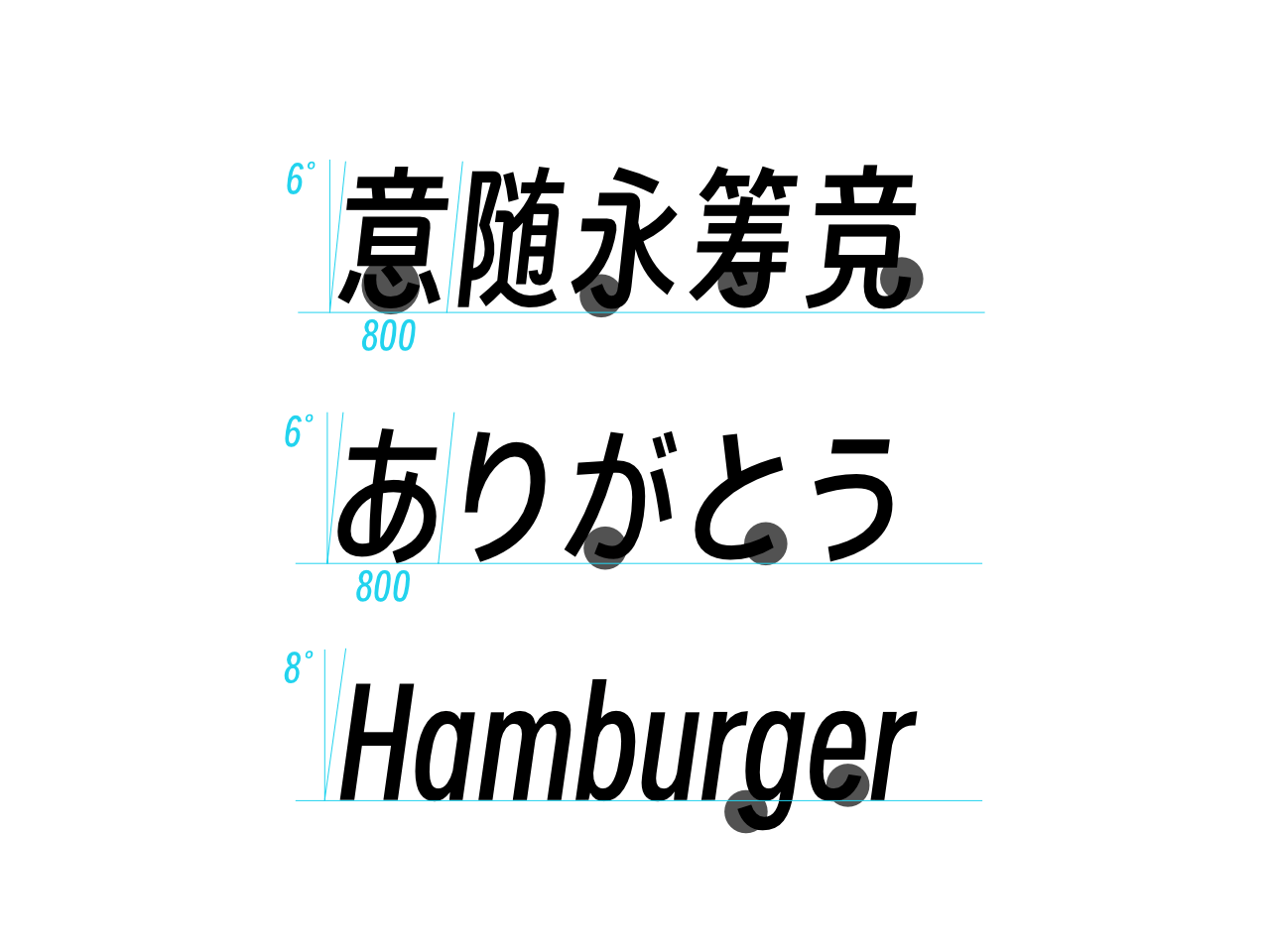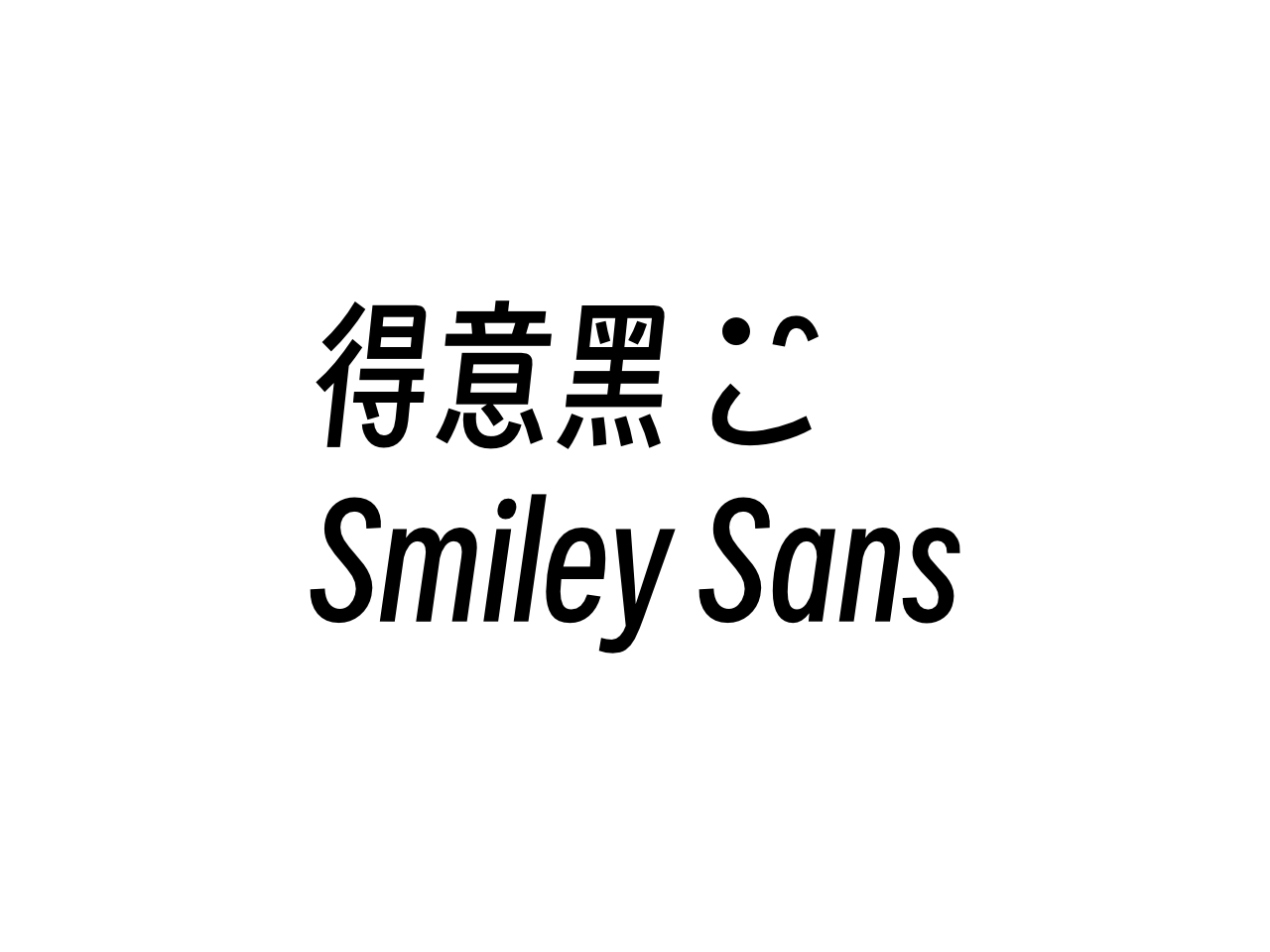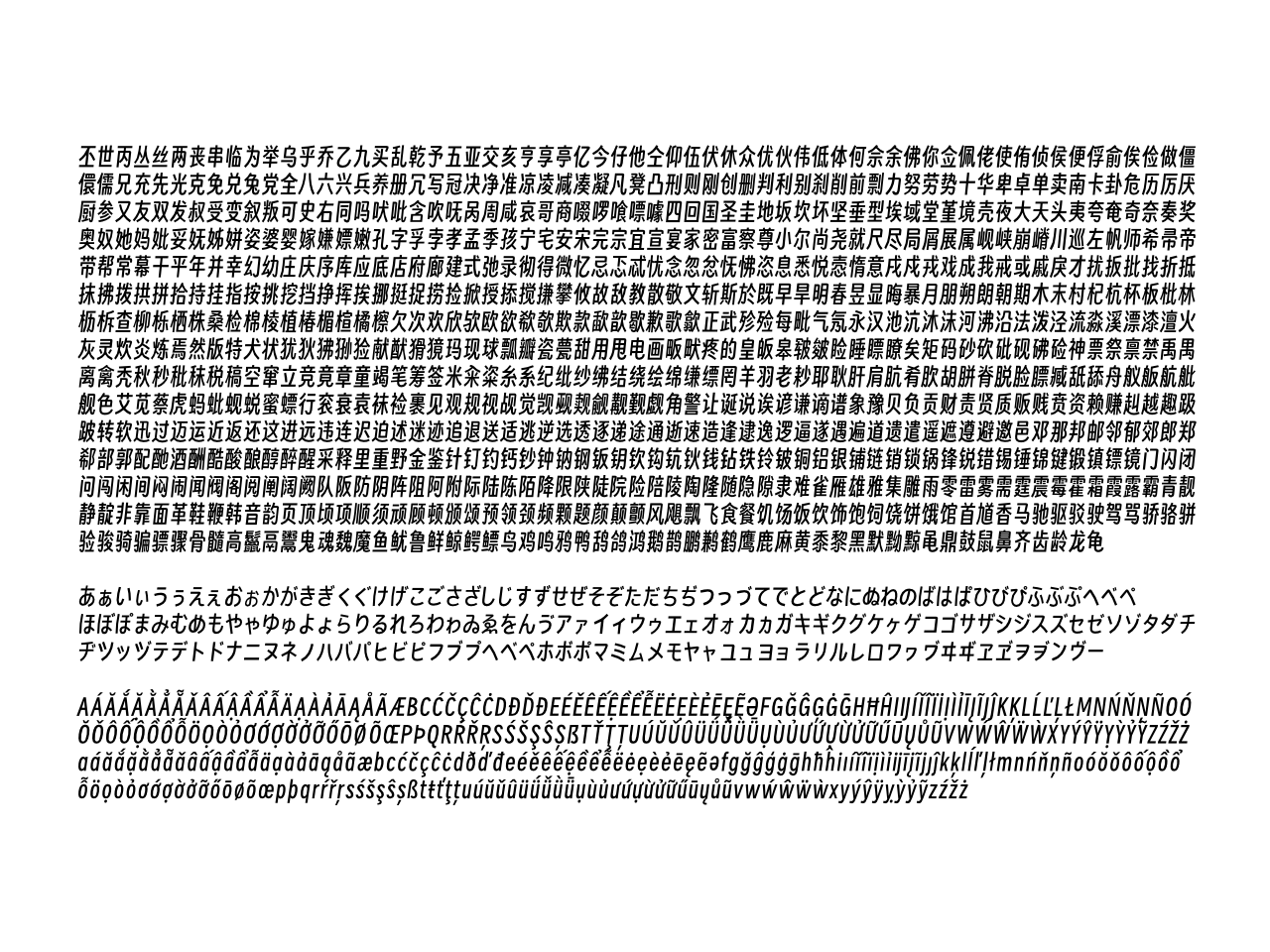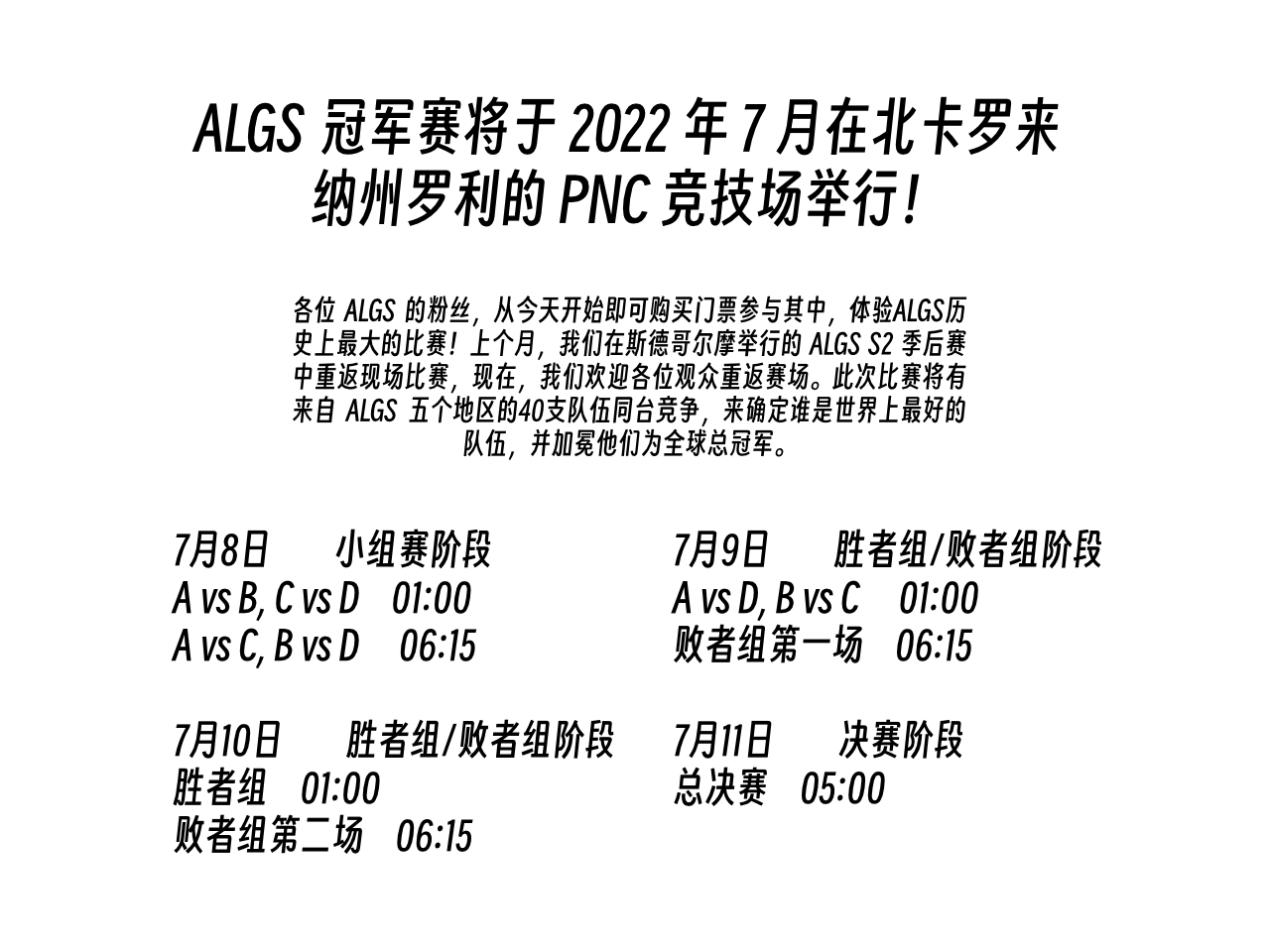
得意黑是一款独具匠心的中文字体,它巧妙地在人文观感与几何特征之间寻求着精妙的平衡。其整体设计赋予了字身一种纤细而略带倾斜的形态,这种独特的视觉比例不仅带来了现代感与动感,也使其在排版中能营造出紧凑而富有节奏的视觉效果。更值得注意的是,字体的诸多细节处匠心独运,融入了取法手绘美术字的特殊造型。这意味着,它在严谨的几何框架之上,增添了来自手绘的、有机的线条变化与笔触韵味,使得字体在规整中透出一股生动的手作温度与艺术气息。在字符覆盖方面,得意黑提供了全面的支持:它完整收录了简体中文常用字,严格覆盖《GB/T 2312-1980》编码字符集以及最新的《通用规范汉字表》,同时涵盖拉丁字母、西里尔字母、希腊字母、日文假名、阿拉伯数字以及各类常用标点符号。这使得得意黑不仅适用于各类中文标题与正文排版,也能轻松应对多语言混排的复杂场景,是一款功能完善且风格鲜明的设计字体。
Smiley Sans 字体标志,包含中文“得意黑”与由字符构成的笑脸符号
字体样本,展示了汉字、平假名以及带有变音符号的拉丁字母。
三种语言文本样本的排版对齐示意图,包含中文、日文和英文,并标注了倾斜角度和行高测量值。
2022年7月ALGS冠军赛将在北卡罗来纳州罗利PNC竞技场举办,欢迎粉丝购票参与,同时公布7月8日至11日的小组赛、胜者组/败者组、决赛阶段赛程安排。